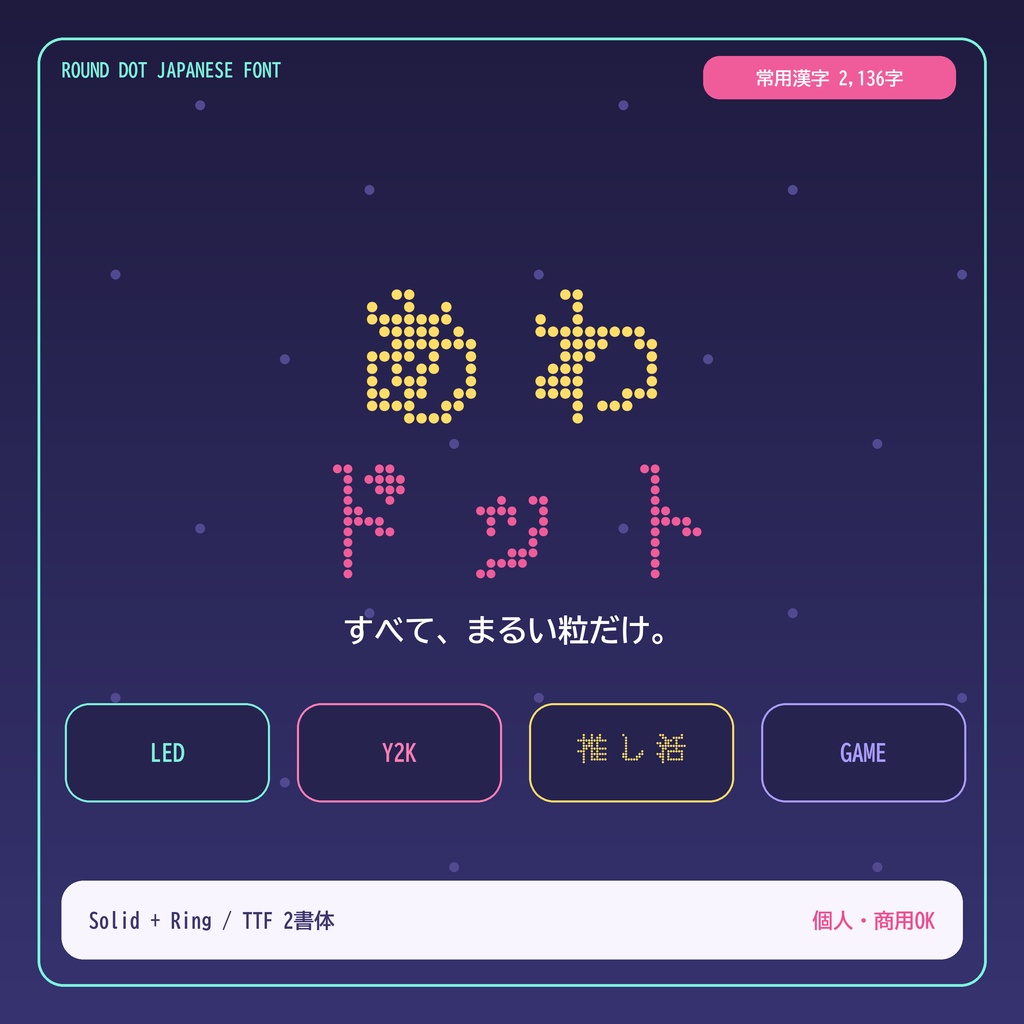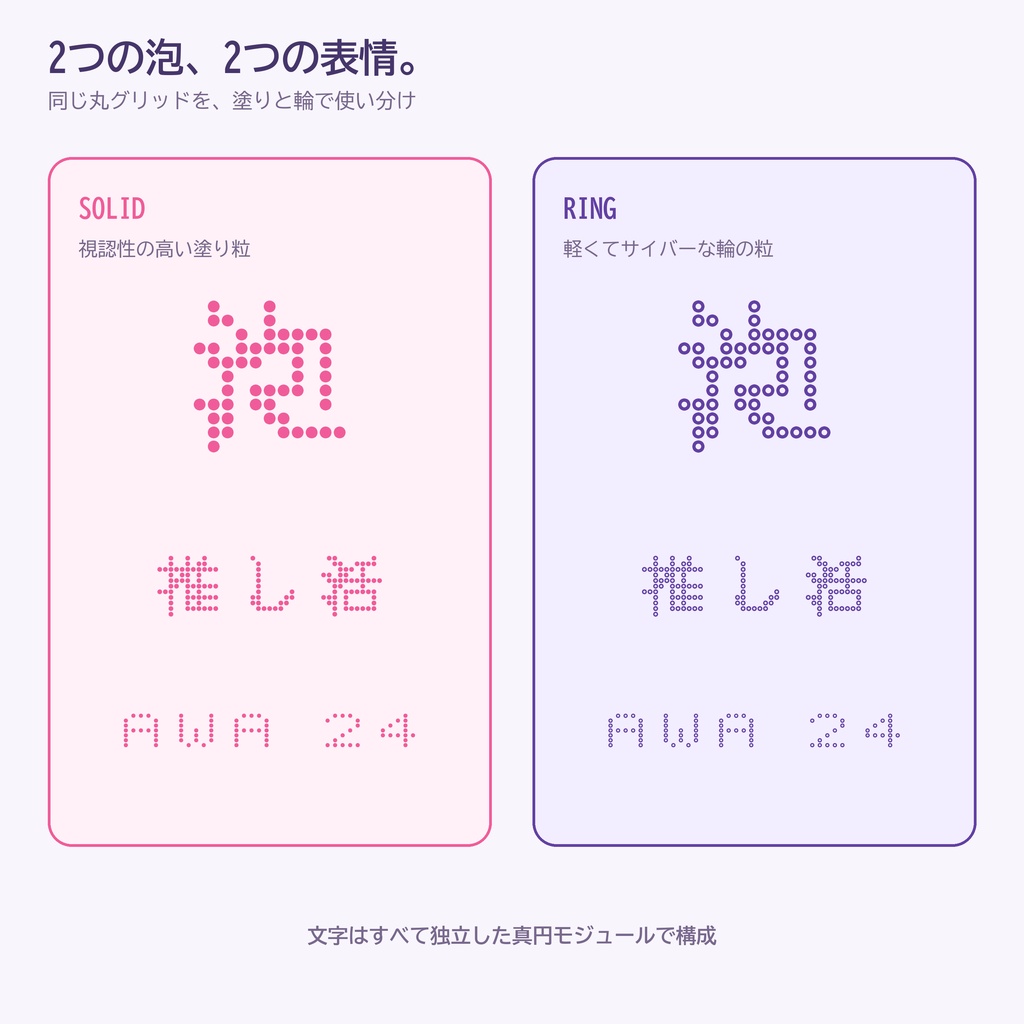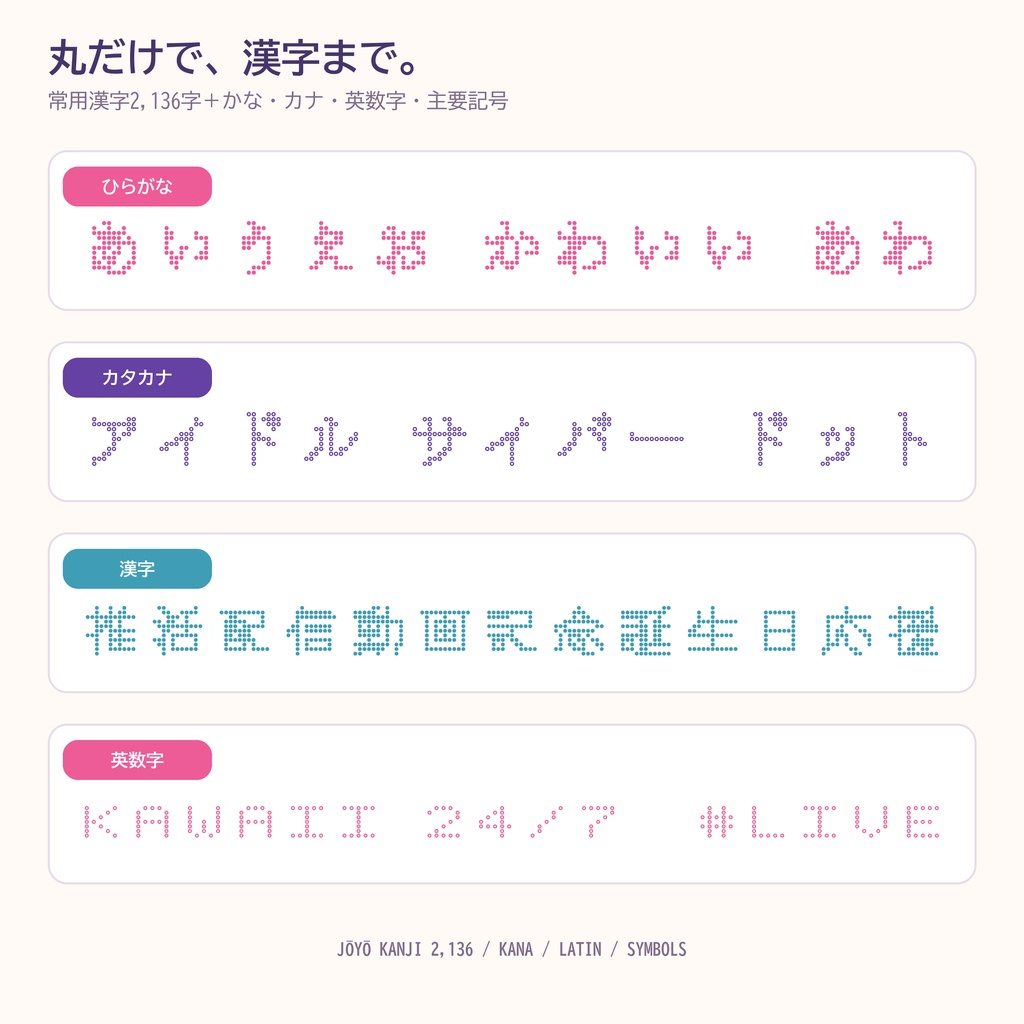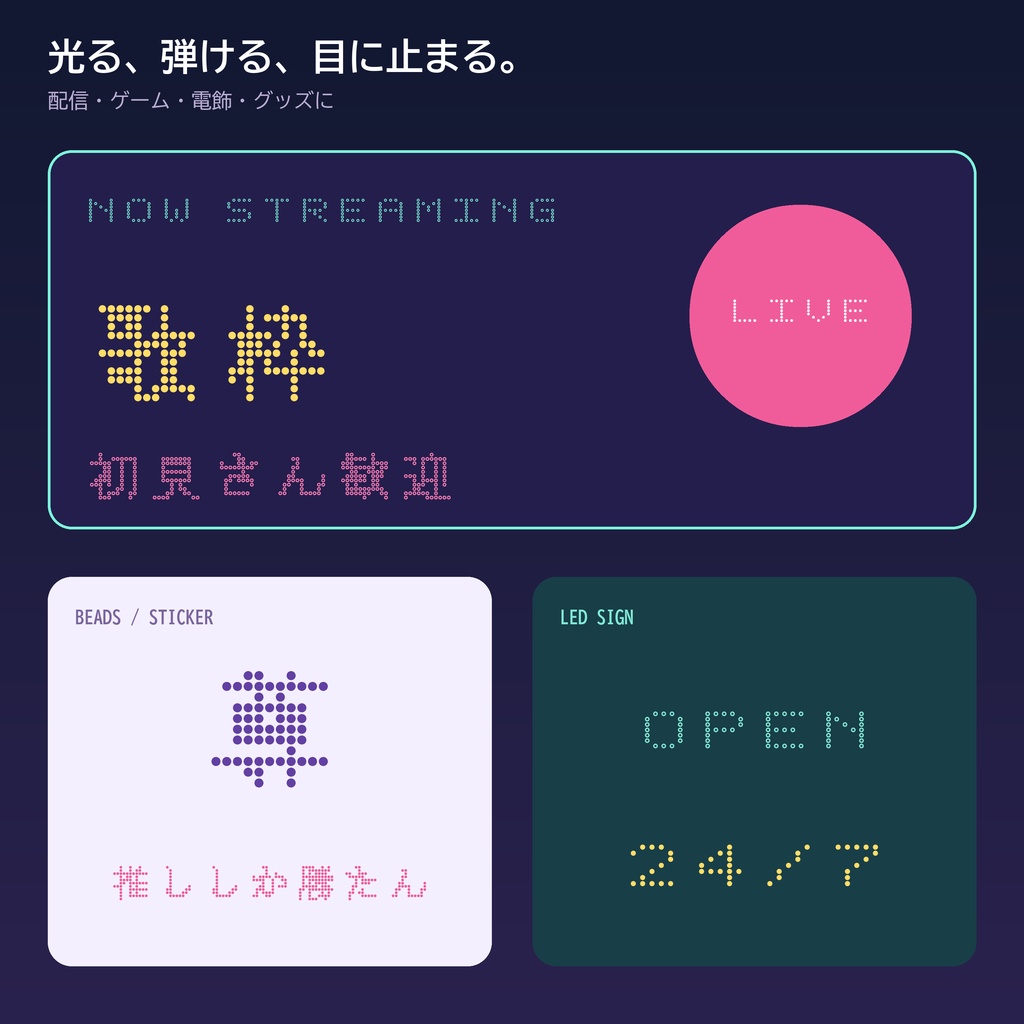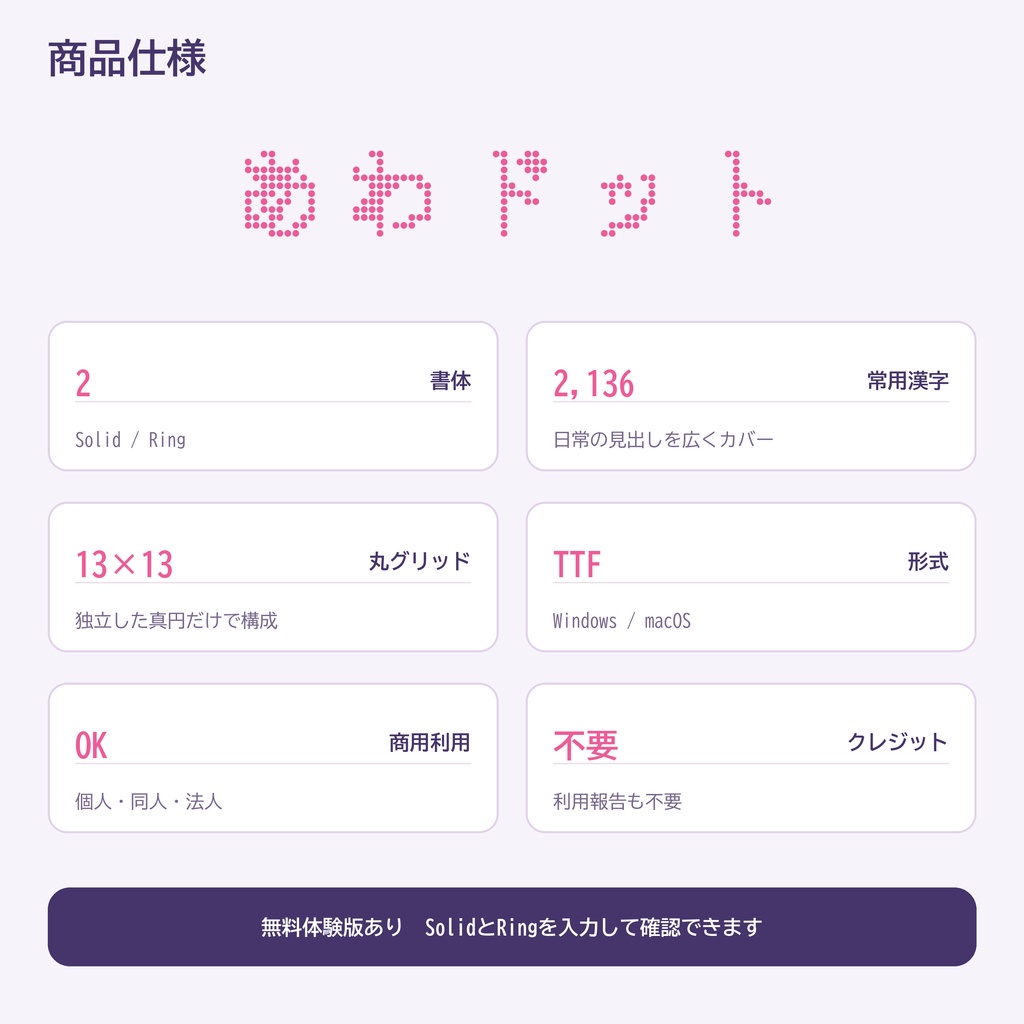
【常用漢字・丸ドット】あわドット|LED・Y2K・推し活向け日本語フォント2書体
文字を、まるい泡の粒だけで。 「あわドット」は、すべての字形を独立した真円モジュールで組み直した日本語ディスプレイフォントです。 一般的なピクセルフォントの四角いマスではなく、13×13グリッド上の丸い粒だけで構成。LED看板、ビーズ、電飾、Y2K、レトロゲーム、推し活画像など、デジタルなのにやわらかい表情を作れます。 ■ 2つの書体 ・Solid:粒を塗りつぶした、視認性の高い基本書体 ・Ring:粒を輪にした、軽くてサイバーな装飾書体 ■ 収録 ・常用漢字 2,136字 ・ひらがな、カタカナ、英数字、主要記号 ・TrueType(TTF)2書体 ■ おすすめ用途 配信サムネ/VTuber・推し活/MV・歌詞/LEDサイン/ゲームUI/同人誌/ステッカー/ビーズ図案/SNS告知/ロゴ ■ 利用条件 個人・商用OK、クレジット不要。ロゴ、グッズ、動画、ゲーム、同人作品、クライアントワークに利用できます。フォントファイルそのものの再配布・共有・転売は禁止です。 ※本文ではなく、大きな見出しや短いコピー向けです。 ※GlyphWiki由来のKAGEデータは13×13の占有情報へ変換し、元の線幅・端部・輪郭を使用せず、独立した真円だけで再構築しています。GlyphWikiライセンス原文を同梱しています。